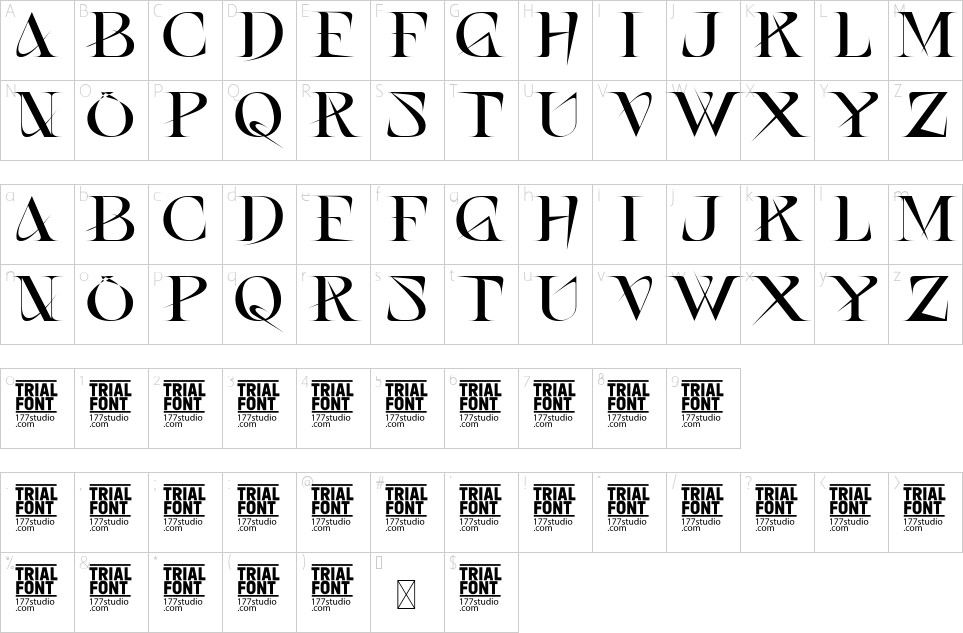
Descubra a elegância e a sofisticação da Across Corner font, ideal para personalizar textos de maneira única e moderna. Desenvolvida pelo estúdio 177studio.com, esta fonte oferece um design arrojado e versátil, perfeito para um amplo range de projetos de design gráfico. Com um download de 802 vezes, você pode estar certo de que este é um recurso gráfico de qualidade que será útil para muitas ocasiões. Adquira já a Across Corner font para adicionar um toque diferenciado a seus projetos de design gráfico, seja em suas tarefas diárias ou projetos profissionais. Esta fonte é ideal para web, design gráfico digital, impressão, gráficos de mídia, identidade visual, design de logotipos, criação de materiais de publicidade, design de páginas web, ilustrações digitais e muito mais. Com Across Corner, sua criatividade e estilo gráfico ganharão uma nova dimensão.